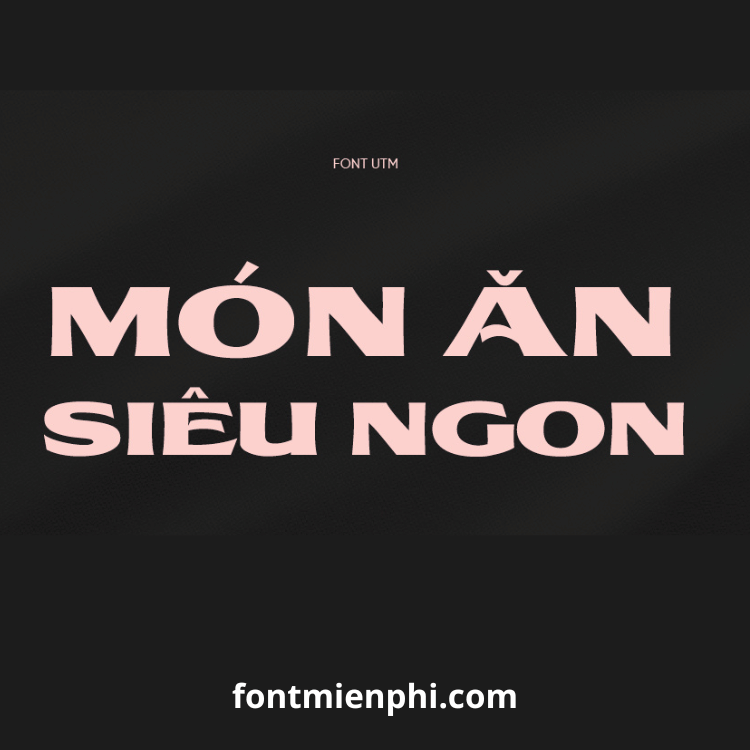
Font Việt hóa UTM Kona KT
Mô Tả Chi Tiết Font Việt Hóa “UTM Kona KT”
1. Giới Thiệu
UTM Kona KT là một font chữ sans-serif hiện đại với thiết kế mạnh mẽ, góc cạnh nhưng vẫn giữ được nét tinh tế. Font mang phong cách urban, thể thao và công nghệ, phù hợp cho các thiết kế logo, game, poster động lực, branding cá tính và các dự án cần sự khỏe khoắn, nam tính.
2. Đặc Điểm Nổi Bật
✔ Phong cách hiện đại, góc cạnh: Nét chữ dày, vuông vức, tạo cảm giác mạnh mẽ và chắc chắn.
✔ Đa dạng ký tự: Bao gồm chữ hoa, chữ thường, số và các ký tự đặc biệt.
✔ Dễ đọc, dễ ứng dụng: Phù hợp cho cả tiêu đề lớn và text ngắn trong thiết kế.
3. Ứng Dụng Phổ Biến
• Thiết kế thể thao, game, esports (logo đội tuyển, banner game).
• Poster động lực, slogan mạnh mẽ.
• Thiết kế áo thun, phụ kiện streetwear.
• Branding công nghệ, startup năng động.